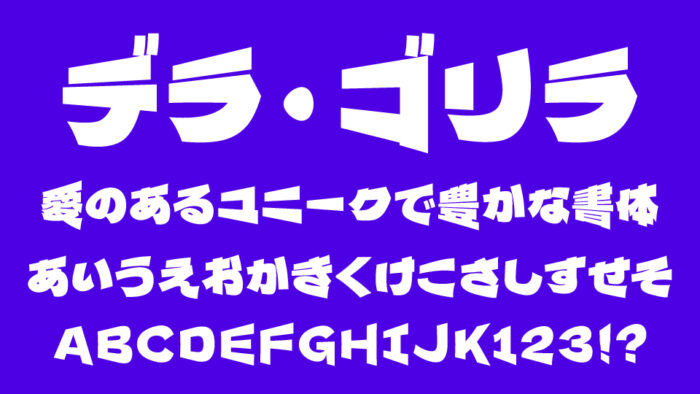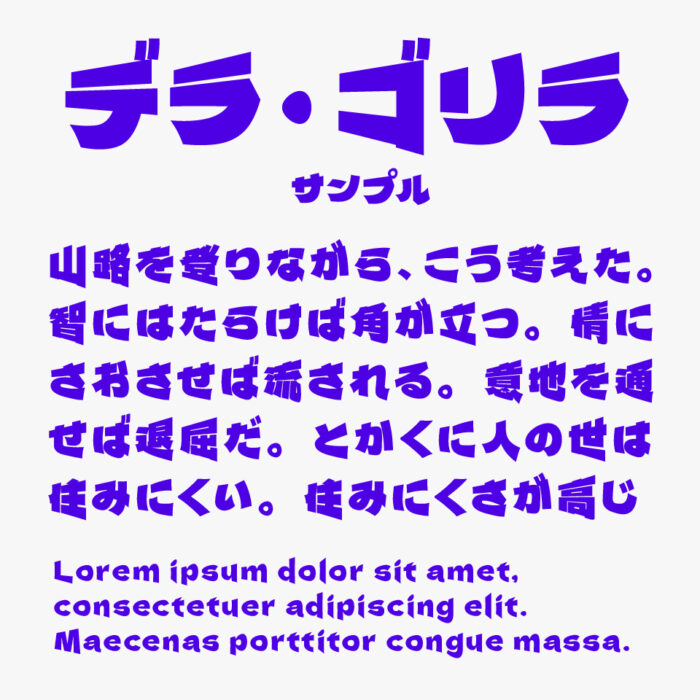
デラ・ゴリラフォントは、デラゴシックフォントをベースに、左側がギュッと傾いた加工が施されたユニークな文字形のデザインフォントです。
フォント名がユーモラスなのありますが、フォルムが強烈な印象で、角張った部分と曲線のアンバランスさも特徴で、豪快で破天荒なキャラクター性を感じるデザインフォントです。
コミカルでインパクトのある雰囲気なので、見出しやタイトルなどにもぴったりなフォントです。
デラ・ゴリラ